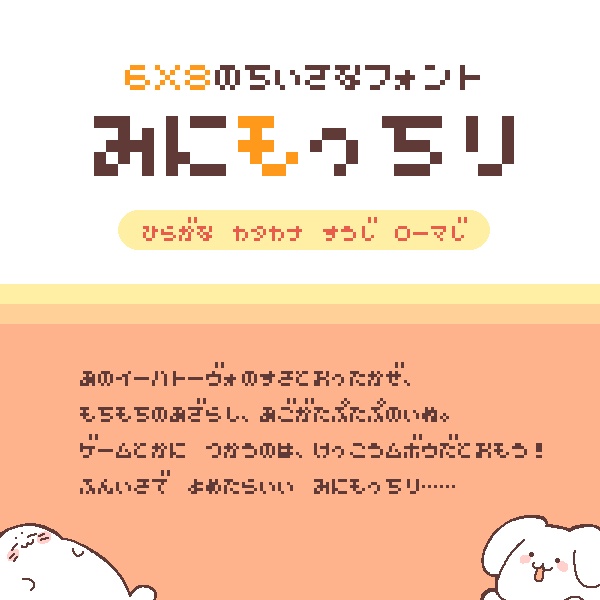
マテンロウ計画6×8のちいさなフォント「みにもっちり」Digital0 JPY免費下載みにもっちり.zip (9.2 KB)みにもっちり.zipAbout Gift5×5ピクセルフォントチャレンジで描いたフォントをフォント化しました。 8px指定すればきれいに使えるはずです。 こんなときに便利!! ・5ピクセルのフォントをいちいちかくのがめんどくさい 利用規約!! ・このフォントそのものを商売に利用するのはダメです (フォント使った創作の品を売るとかは大丈夫) ・自作発言はダメですマテンロウ計画Visit FANBOX!Tabletop RPGワンダーオブワンダラーシナリオパックマテンロウ計画0 JPYIllustration & CG collections代筆屋ワールドワード 人物図鑑&アートワーク(pass有)マテンロウ計画0 JPYIconsちびコマドット絵作成機マテンロウ計画500 JPY~Iconsちびコマモンスター素材マテンロウ計画500 JPY~Materials (Other)【一部無料】ドット絵部屋素材セット【ココフォリア】マテンロウ計画200 JPY~Materials (Other)【ドット絵】パソコン画面風素材セット【ココフォリア】マテンロウ計画200 JPYTabletop RPG【無料】既存PCで遊ぶプチRPルーム「ふしぎなお菓子を食べるだけ。」マテンロウ計画0 JPYTabletop RPGワンダーオブワンダラーミニサプリ本 ラブアンドワンダーランドマテンロウ計画300 JPYTabletop RPGシティ・ポップ・ファンタジーTRPG ワンダーオブワンダラーマテンロウ計画2,000 JPYTabletop RPG既存PCで遊ぶ小話生成TRPG「かけひきの時間です」マテンロウ計画200 JPYTabletop RPGDead or AliCeサプリメント 赤と白の鏡騒劇マテンロウ計画1,800 JPYTabletop RPGデスゲーム×ファンタジーTRPG Dead or AliCe 基本ルールブックマテンロウ計画1,600 JPY查看更多